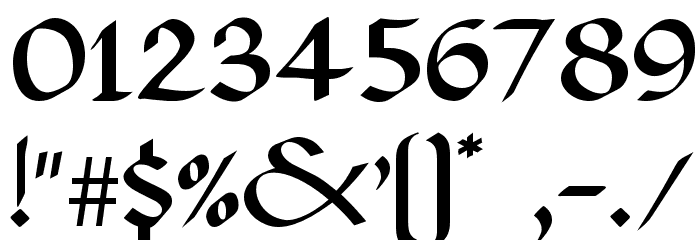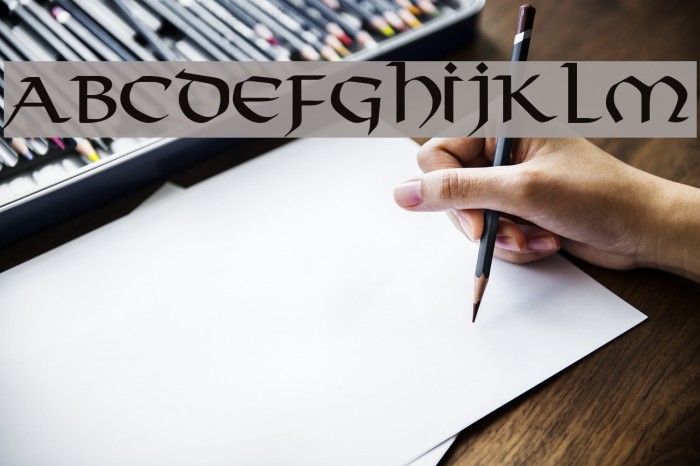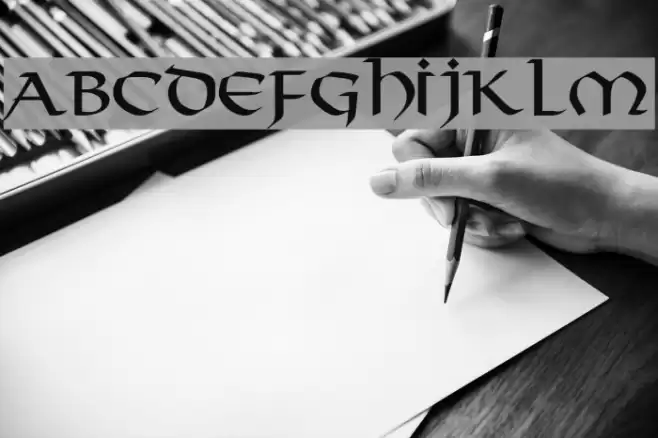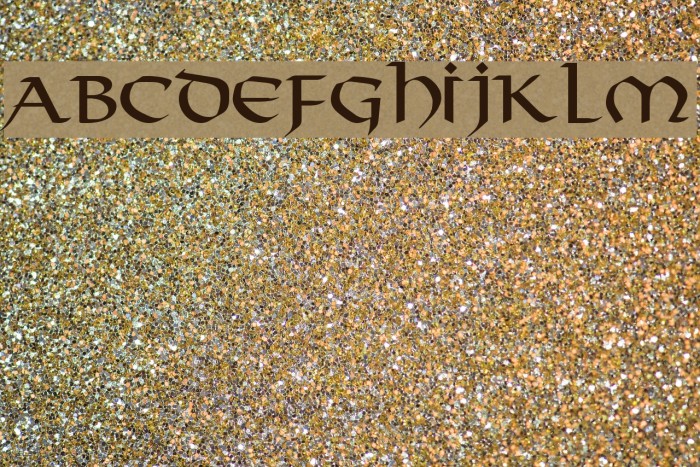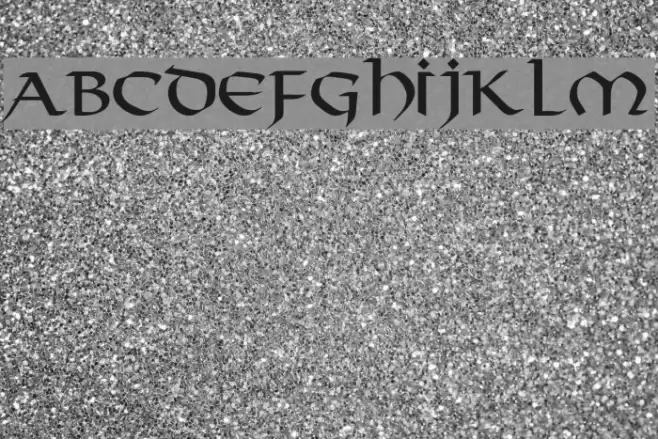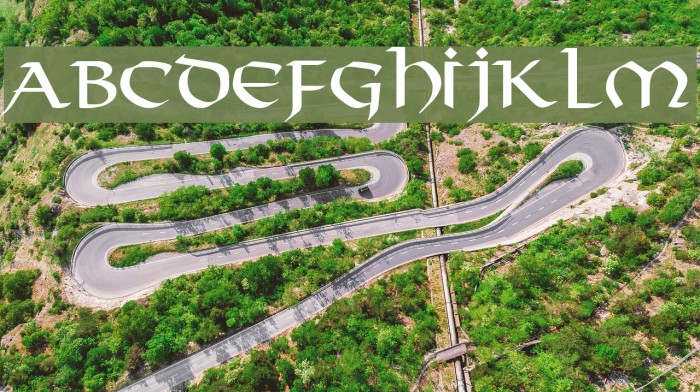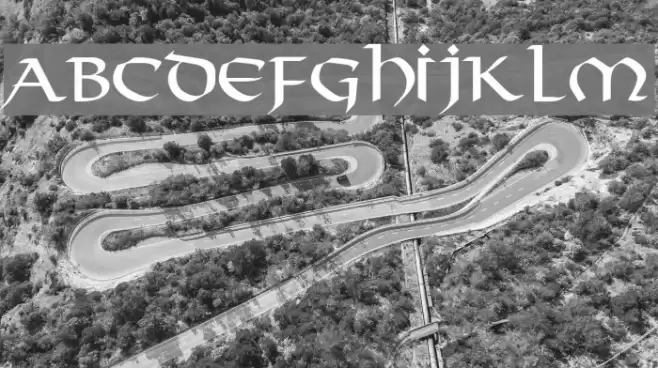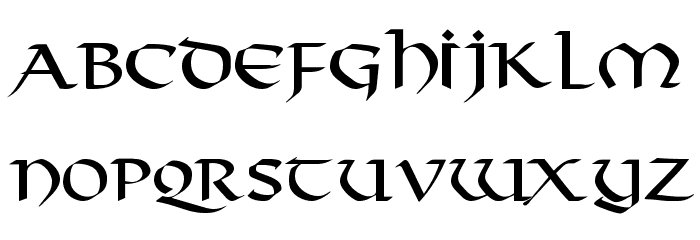
Viking Font
| Proiecte propuse | Ideal for projects that require a historical or fantasy theme, such as book covers, movie posters, or themed event invitations. |